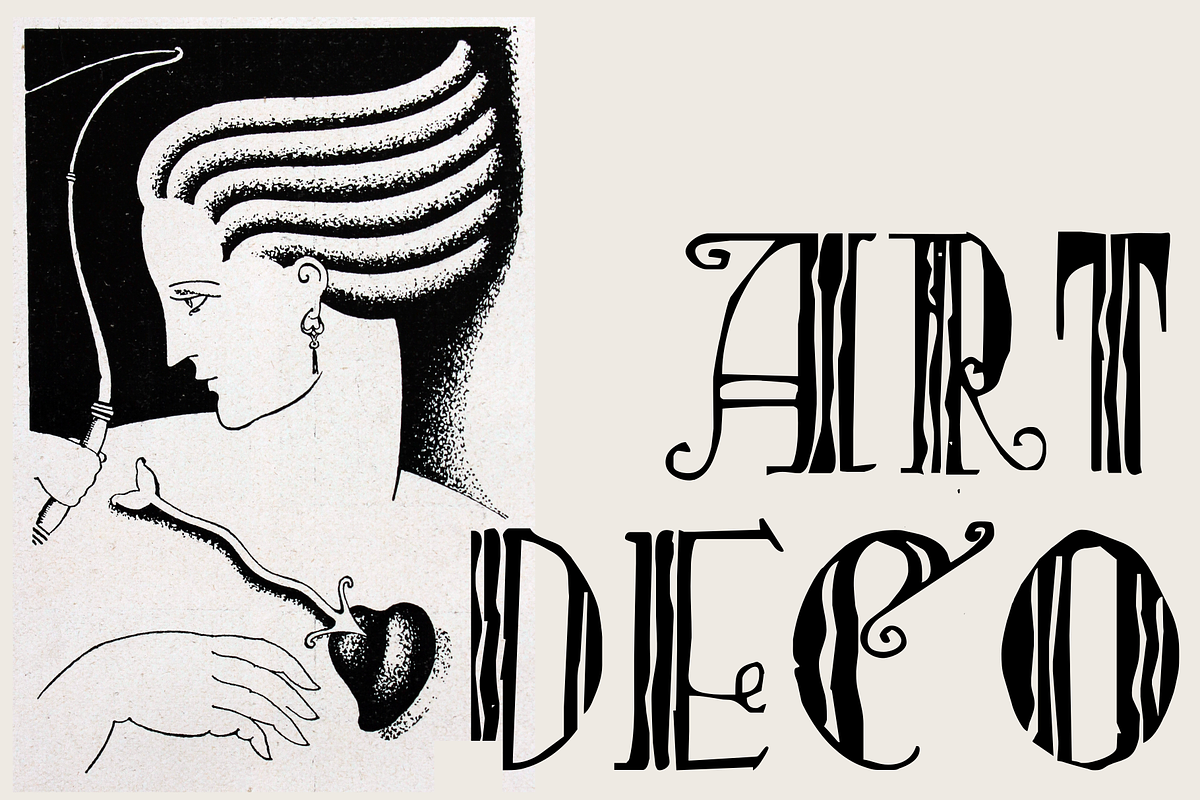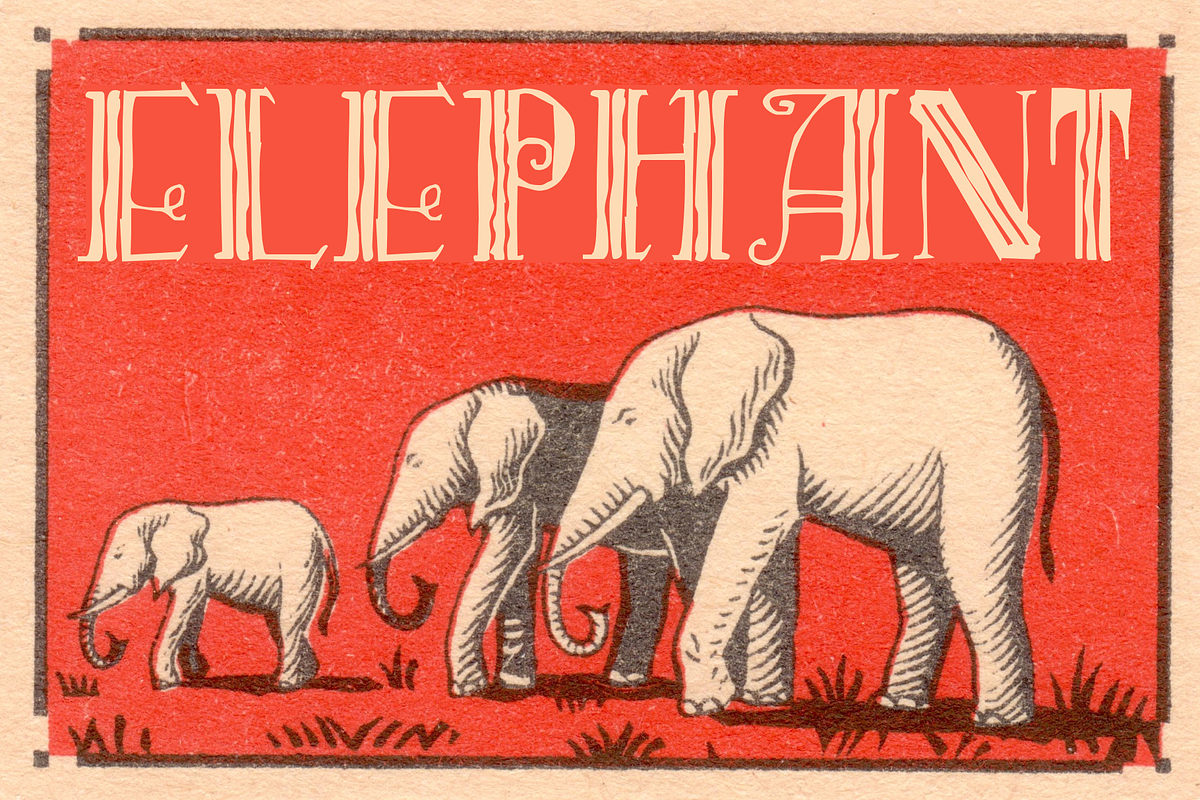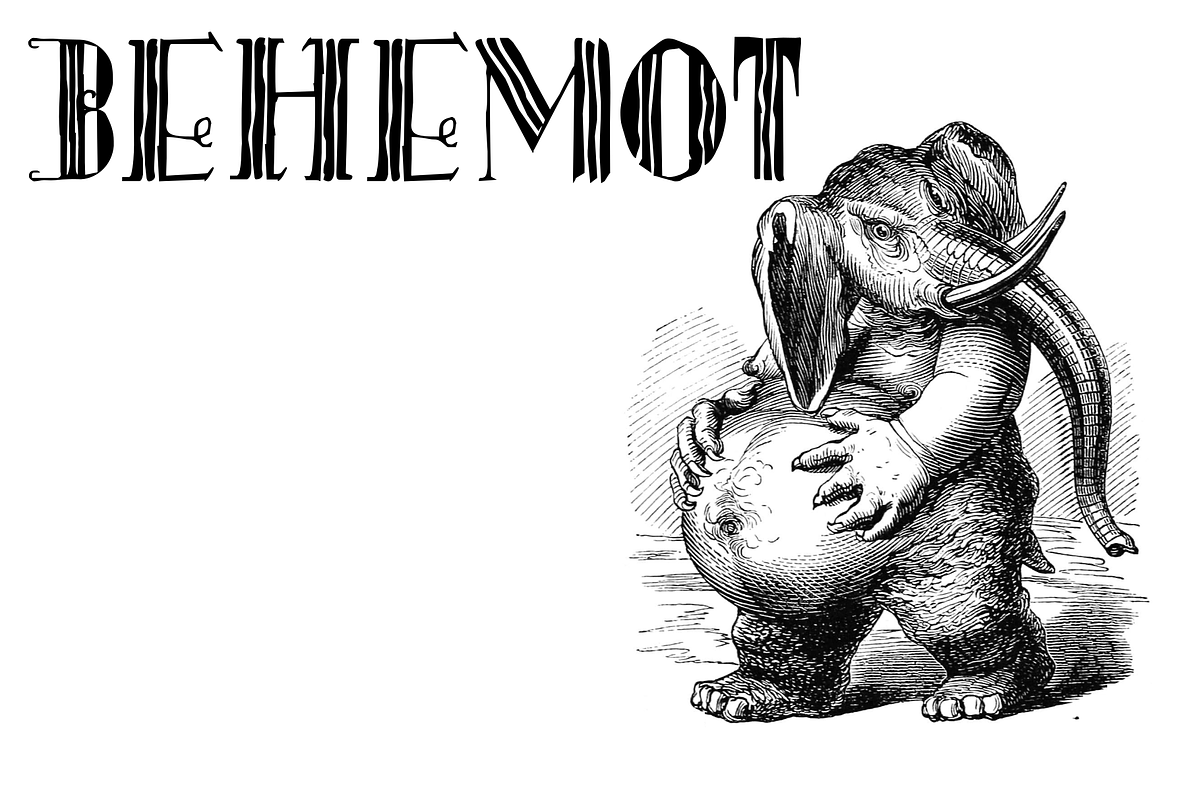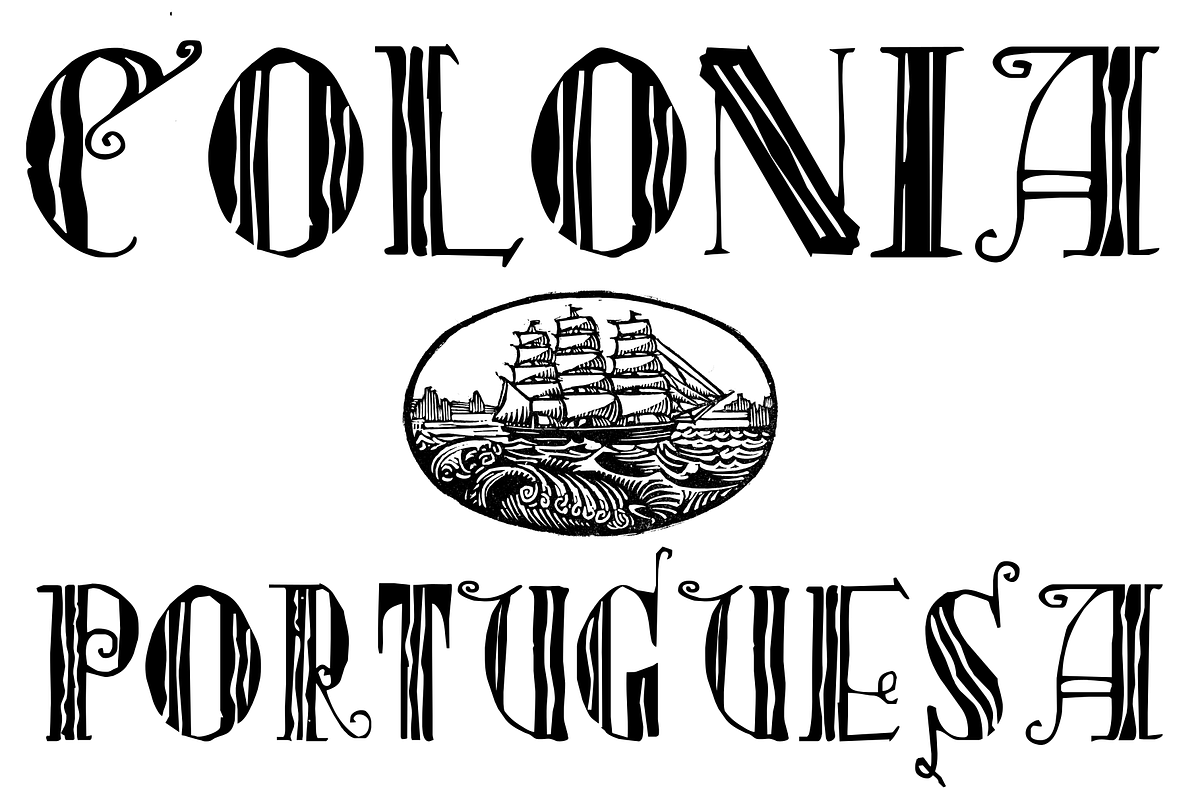
Colonia Portuguesa
A Intellecta encontrou junto ao Gabinete Portugues de Leitura do Recife o "Album da Colonia Portuguesa", uma edição das primeiras décadas do século passado, impressa no Brasil, e que as primeiras leituras indicam tratar-se de um periódico que comentava a vida social dos Portugueses (do embaixador aos comerciantes e pessoas da sociedade de então) em terras brasileiras.
Para o desenvolvimento de novas fontes embasadas é material primoroso, que mescla diversos estilos art-déco, art nouveau, capitulares góticas e romanas, fleurons, bordas, enfim, uma profusão de adornos muito comuns à época neste tipo de publicação. Não há esmero tipográfico nem rigor técnio há, de fato, pouco uso de tipos móveis padrão), o jornal parece ter sido diagramado e leterado por artistas locais (portugueses ou não) que desenhavam as letras (letristas).